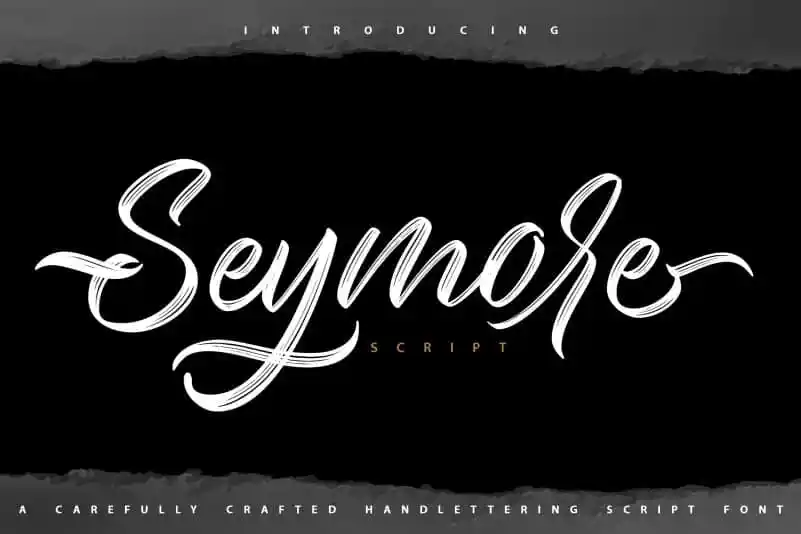
Seymore Brush Font – Download Grátis
A fonte ‘Seymore Brush Font’ é uma elegante tipografia feita para projetos de design especializados no app perfeito de pincel. Desenvolvida pela Type Factory, essa elegante criação foi idealmente criada para dar um toque sofisticado aos seus materiais de marca e design. Suas linhas fluidas e sua aparência única fazem dele uma escolha impressionante para qualquer projeto que você esteja trabalhando na categoria de fontes script. Utilizada como fonte, ela pode reforçar o seu desafio de criar um design único e inovador, sem dúvida deixará uma impressão poderosa em seus seguidores ou clientes. Ideal para designers que buscam algo diferente e sofisticado para dar um toque final aos seus projetos, ‘Seymore Brush Font’ é uma escolha inteligente para quem busca trazer vida à sua identidade visual.